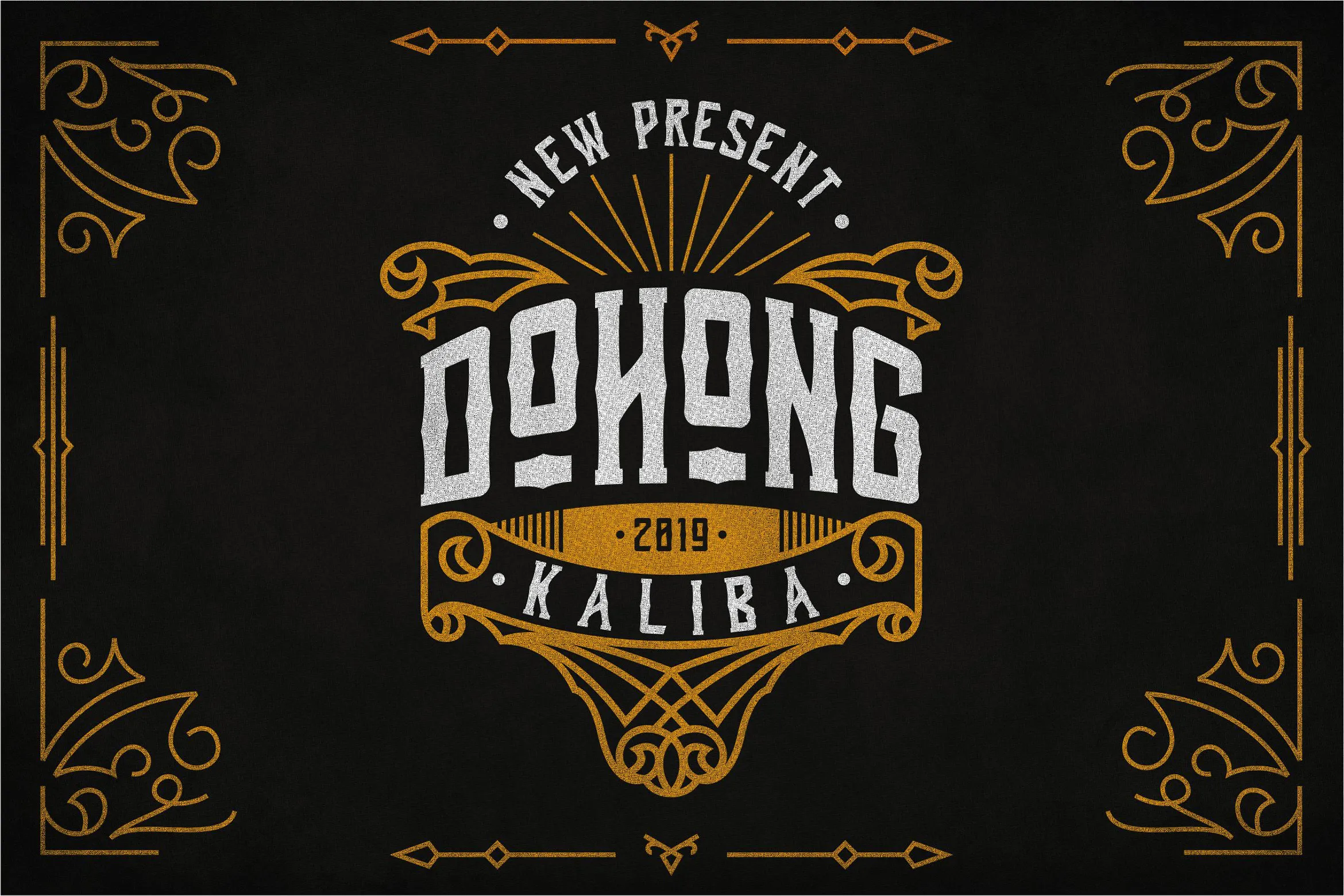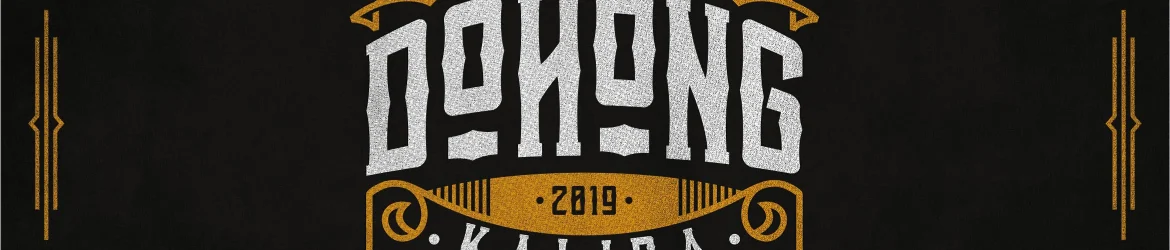
Dohong Kaliba Vintage Font – Download Grátis
A fonte “Dohong Kaliba Vintage” é uma criação única inspirada em fontes blackletter tradicionais, exibindo características elegantes e sofisticadas que remetem aos posters de propaganda clássicos. Criada a mão por um designer talentoso da inspirasign, esta font se destaca pela sua elegância e profundidade, proporcionando um toque vintage e retrô em qualquer projeto gráfico onde for utilizada. Seja para criar rótulos de embalagens, letras de logotipo ou até mesmo textos em páginas web, “Dohong Kaliba Vintage” oferece uma opção perfeita para quem procura algo singular e único que remeta à década de 1900. Não hesite em experimentar esta fonte vintage para trazer um toque clássico ao seu design.